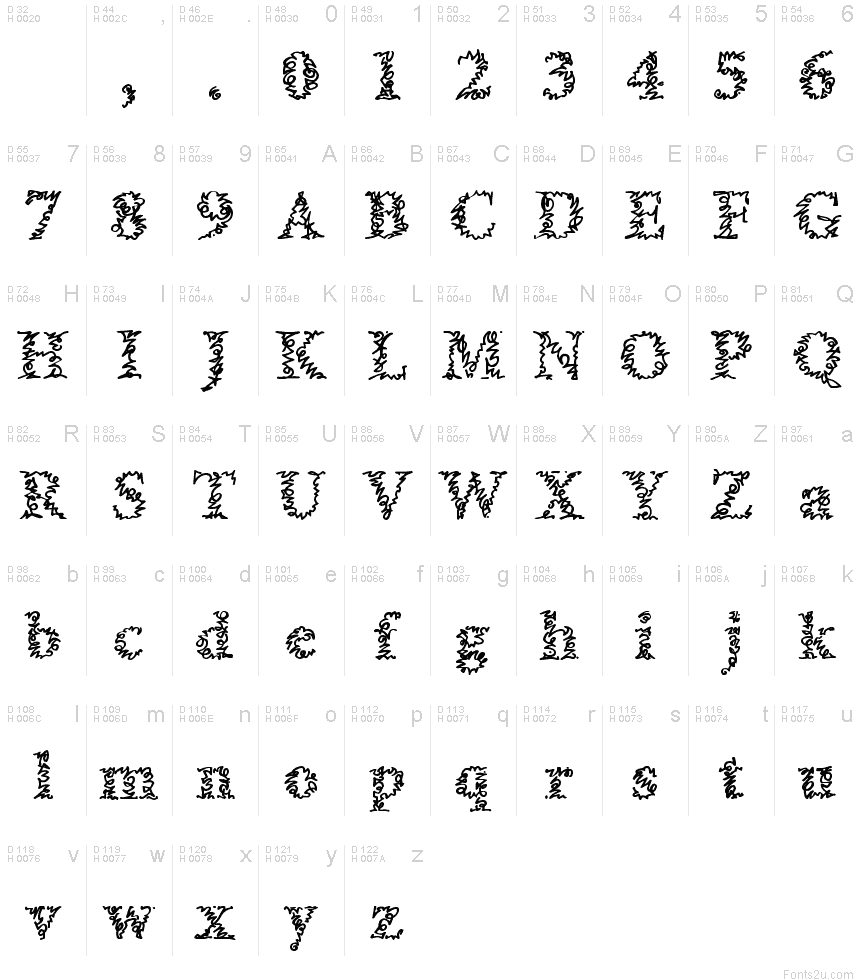
a Morris line 字体
a Morris line
JOEBOB Graphics
JJW van der Ham
“A Morris Line” 出自 J O E B O B graphics,是一款免费的植物主题“垃圾风”字体,带有一种“工艺美术运动”特有的纤细感。字母看起来就像是用笔快速勾勒出的藤蔓,带有粗糙的叶片边缘、环绕的笔触和一种随性而不安的手写韵律,让整款字体显得自由散漫,甚至带点野性。
它非常适合海报、小志(Zine)、专辑封面、活动传单以及各种奇特的包装设计,在这些地方,文字几乎可以作为装饰元素使用。作为一款免费字体,它也很适合用于短标题、标题卡和类徽章式的首字母缩写,特别是当你想要文字呈现出那种纠缠、多刺且略带手工感,而不是规整平滑的效果时。